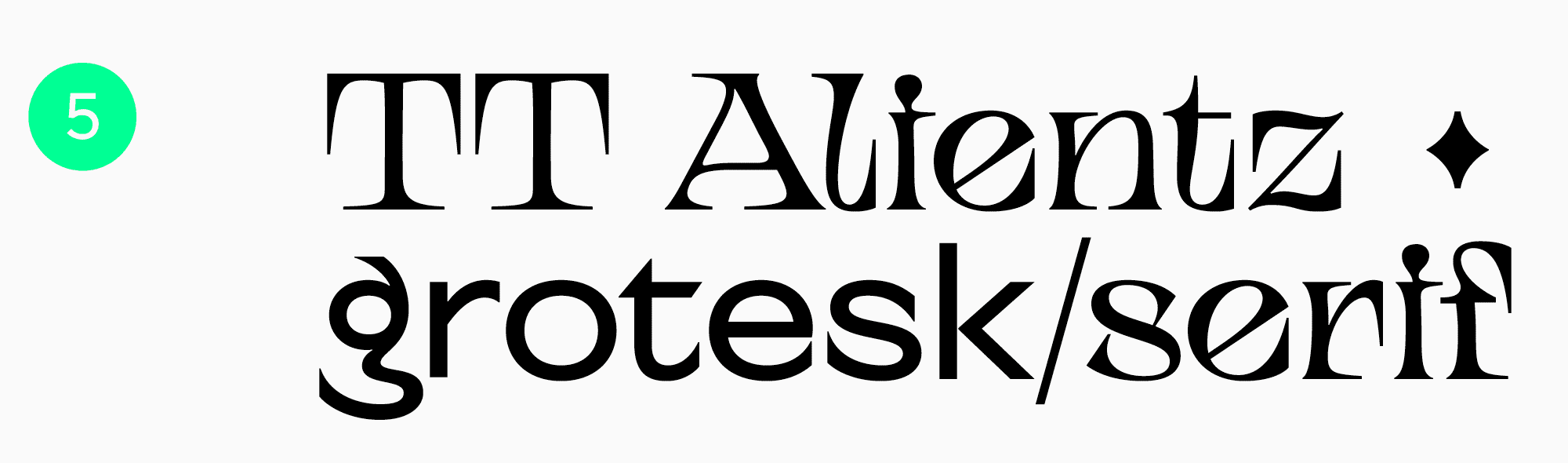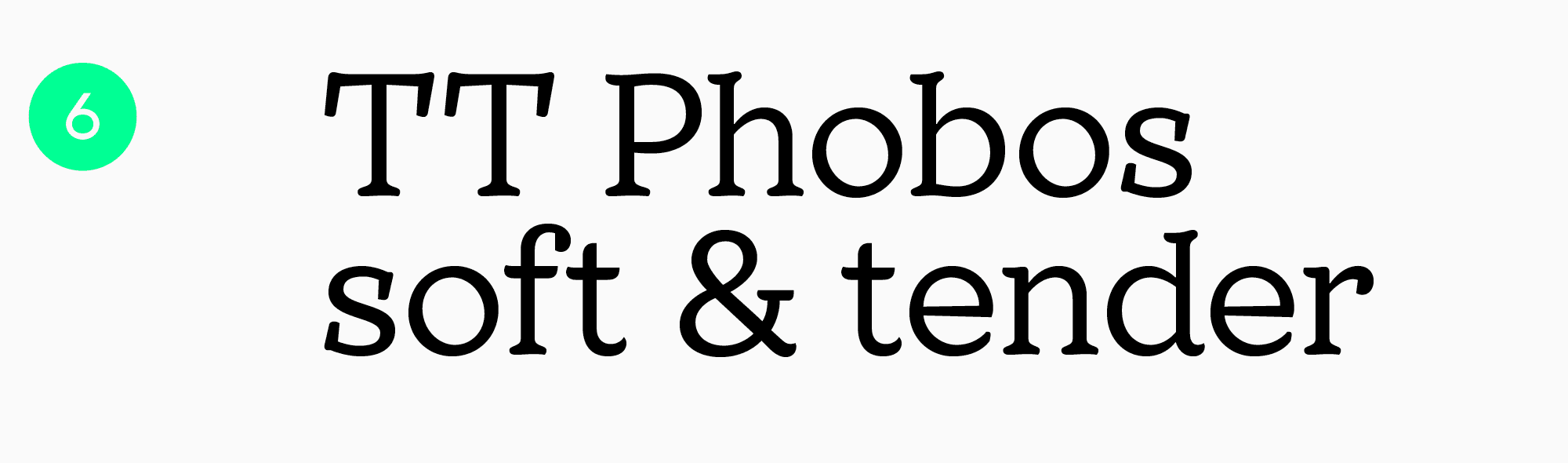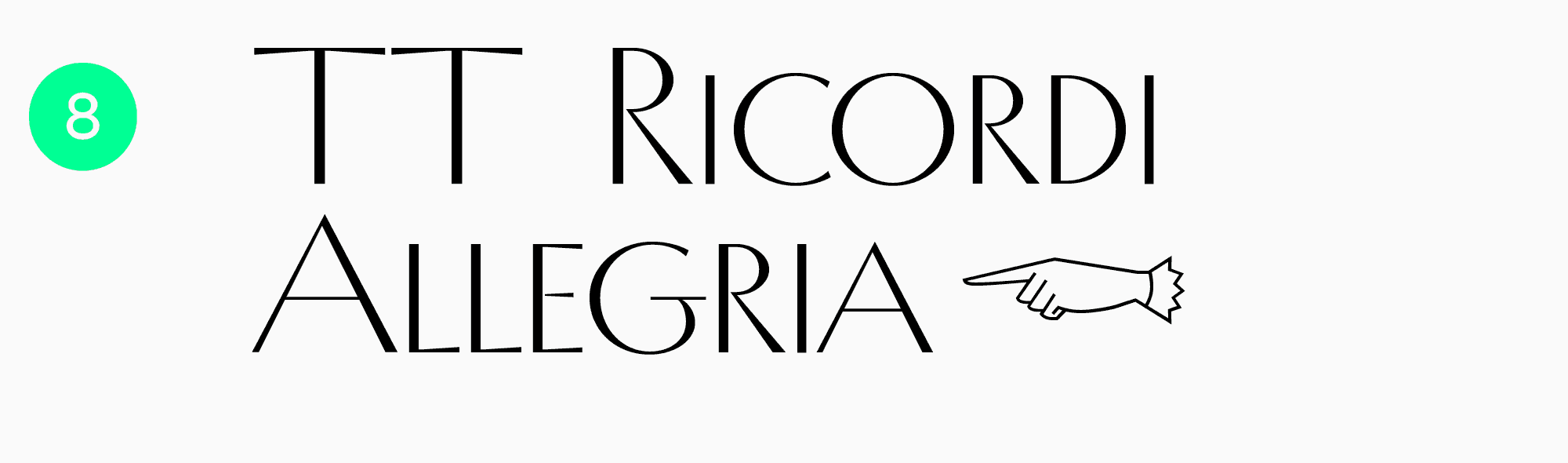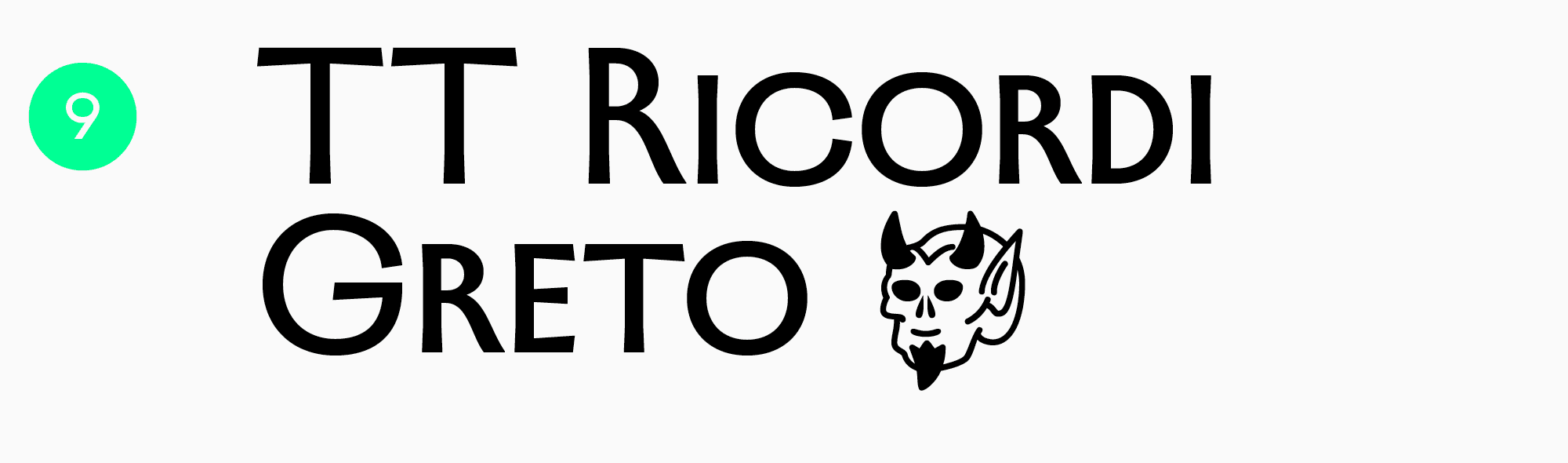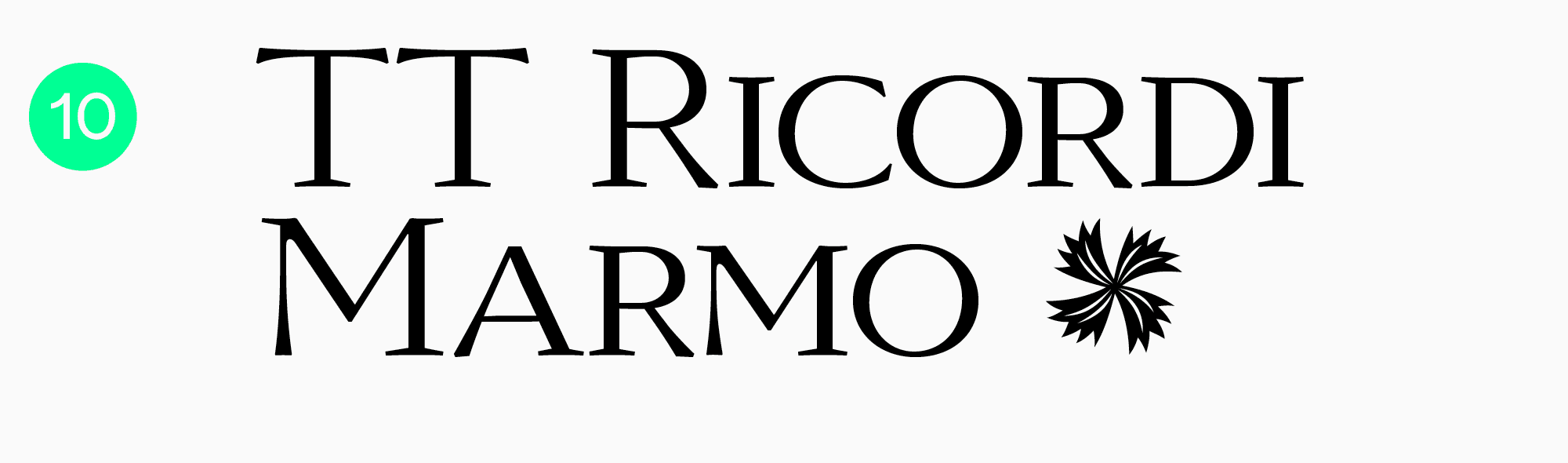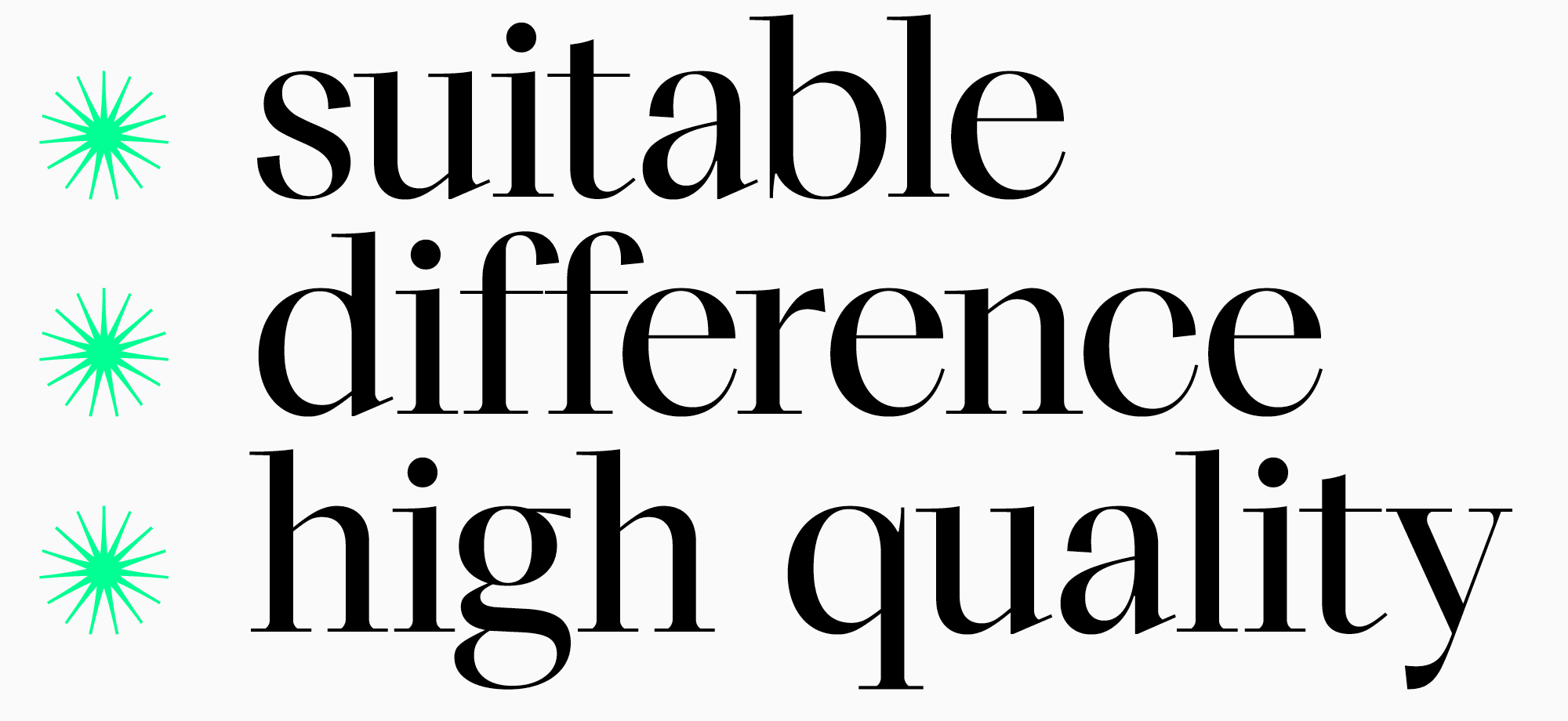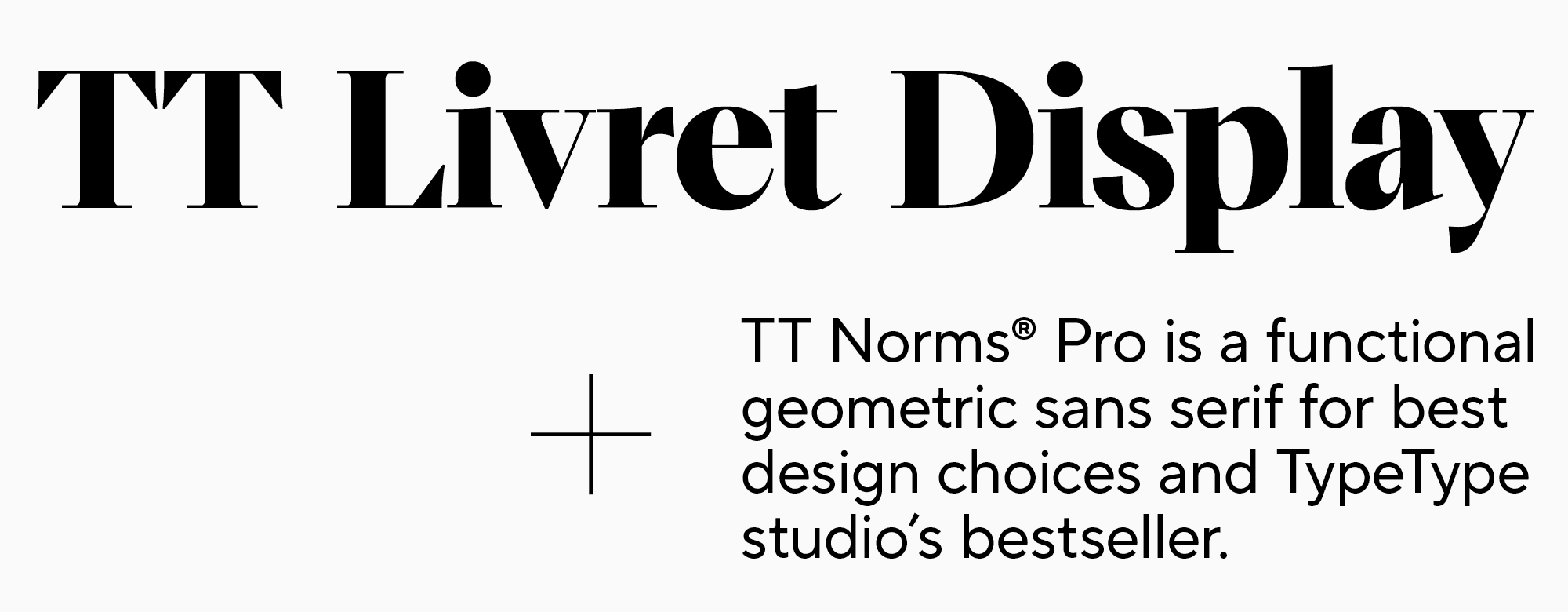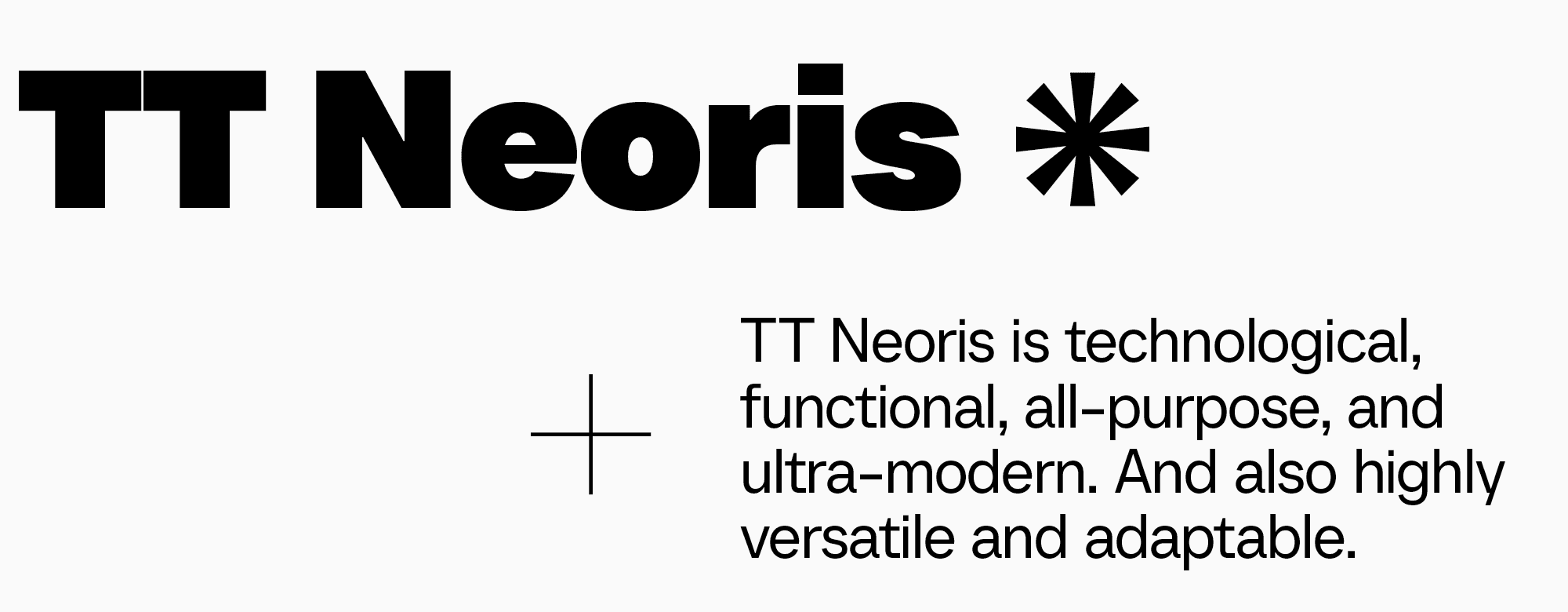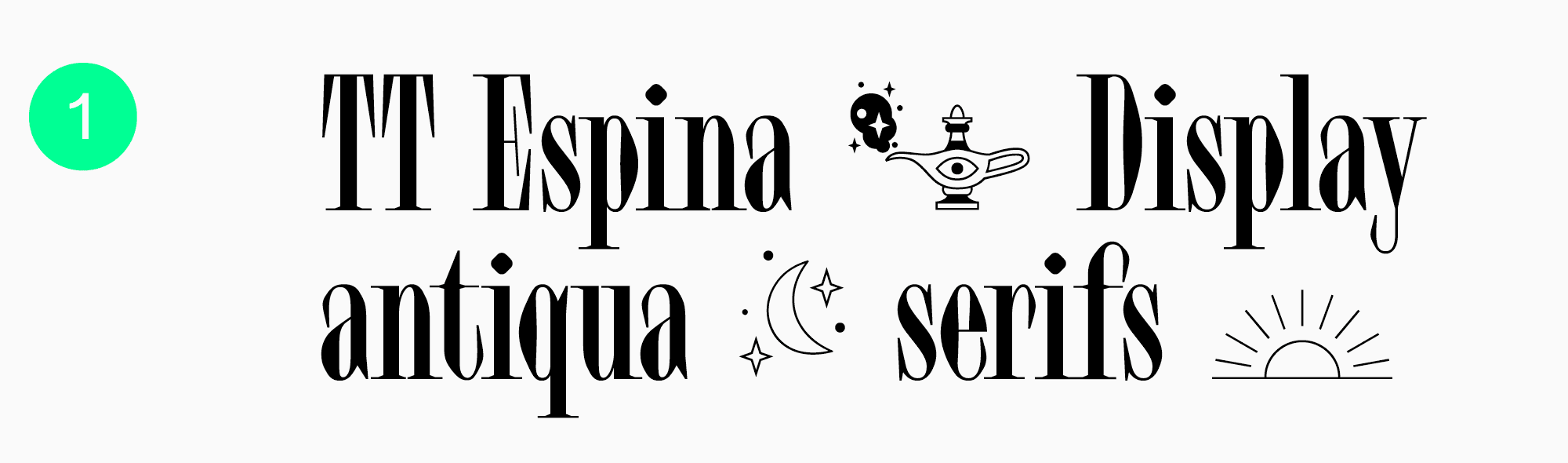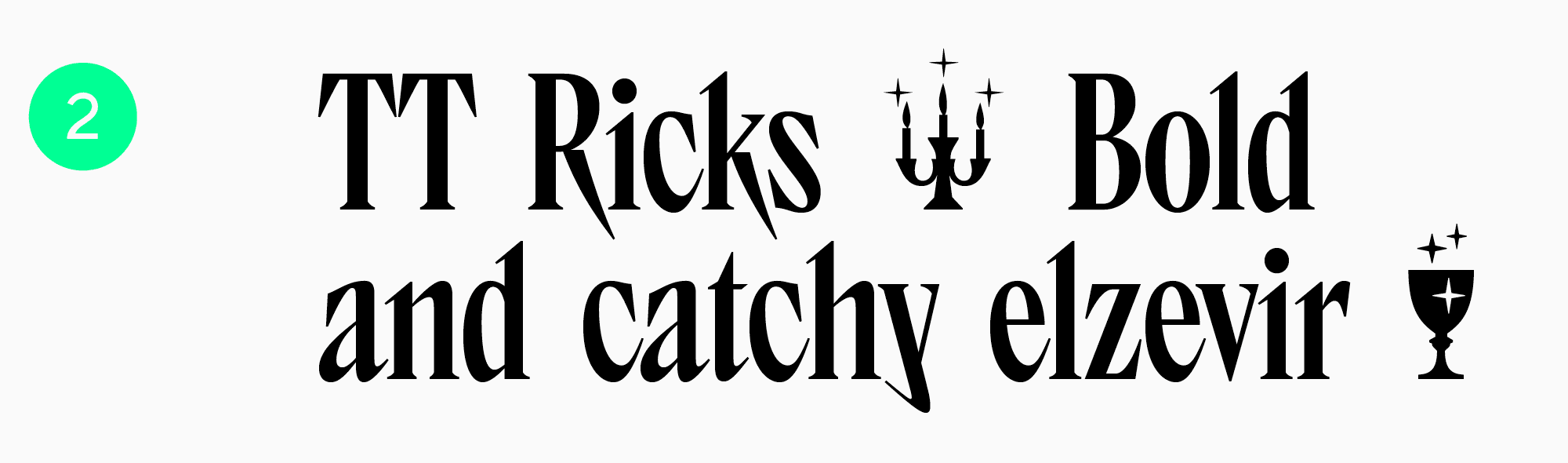
20+ лучших шрифтов для заголовков: ТОП стильных решений
Вступление
Подобрать подходящий шрифт для заголовка бывает непросто. Правильно выбранный акцидентный шрифт будет отражать ценности, идеи и общее настроение всего проекта. Он — та самая «одежка», по которой ваш проект будут встречать. А потому он должен сразу создавать нужное вам впечатление, ведь второго шанса привлечь внимание пользователя в перенасыщенном информацией мире может и не быть.
Какие шрифты для заголовков лучше выбирать и на какие критерии опираться при подборе? Рассказали в этой статье и составили список из 20+ лучших вариантов.
Какие шрифты используются для заголовков?
Все шрифты по назначению делятся на текстовые и заголовочные (акцидентные). Текстовые шрифты подходят для набора больших объемов текста: их должно быть легко и удобно читать на любых устройствах. Они более нейтральные и лаконичные на вид, без лишних деталей. Максимальный комфорт для восприятия — главный критерий при выборе такого шрифта. Текстовые шрифты используются в размере от 6 до 14-16 пунктов.
Акцидентные же шрифты предназначены для крупных надписей, заголовков, акцентов в тексте — в общем, их используют, там, где нужно привлечь внимание. Это более выразительные шрифты с ярким характером. Их графика более сложная, часто они насыщены деталями, которые интересно рассматривать. В отличие от текстовых, акцидентные шрифты используются в более крупном размере — от 14 пунктов.
Среди акцидентных можно выделить титульные шрифты. Они предназначены для оформления титульных листов, обложек и заголовков. Часто у таких шрифтов сокращенных кассовый состав, либо они состоят только из прописных букв. Используются такие шрифты в размере от 16 пунктов.
Интересно, что требования к текстовым шрифтам сформулированы гораздо четче, чем к акцидентным. Скажем больше — благодаря правильной верстке роль заголовочного может исполнить текстовый шрифт. А вот набрать большой массив текста любым акцидентным не получится. Если шрифт был задуман как заголовочный, он, скорее всего, не сможет заменить текстовый.
Получается, что акцидентным может быть практически любой шрифт. Как же тогда выбрать подходящий вариант? Давайте разбираться.
Как выбрать хороший шрифт для заголовка: несколько советов
Выбор шрифта для заголовка — субъективный процесс и напрямую зависит от целей и задач, которые перед вами стоят. Всегда подбирайте шрифт для конкретного проекта, а не просто понравившийся вам визуально вариант. Для разных проектов могут подойти абсолютно разные шрифты, единых правил здесь нет. Однако есть критерии, на которые стоит опираться.
Заголовочный шрифт должен:
• Подходить по стилю для вашего проекта, передавать эмоции и ценности, заложенные в него;
• Отличаться от основного шрифта, чтобы привлекать внимание. То, насколько сильным будет это различие, зависит от ваших целей;
• Корректно отображаться на всех устройствах. Хороший заголовочный шрифт — это технически качественный шрифт. Уделяйте особое внимание этому критерию, если выбираете бесплатный шрифт.
Как выбрать заголовочный шрифт в пару к текстовому?
Если у вас уже есть основной шрифт и вы выбираете к нему в пару акцидентный, либо выбираете шрифтовую пару, рекомендуем ориентироваться на следующие советы.
1. Выбирайте такие шрифты, которые будут эстетически и стилистически подходить для вашего проекта;
2. Определите роль каждого шрифта: какой будет основным, а какой — использоваться для акцентов? Сначала подберите «рабочую лошадку», а уже затем — акцидентную пару к нему;
3. Следуйте принципу максимального контраста. Шрифты в паре должны объединяться идеей, но при этом заметно различаться.
Если вы хотите узнать больше о принципах подбора и сочетания шрифтов, читайте нашу статью «УниверситеТТ: Урок 5. Подбор и сочетание шрифтов: теория и практика».
Процесс подбора шрифтовой пары можно сравнить с выбором наряда. Предположим, вы идете на какое-то мероприятие и в качестве базы надеваете простые джинсы. В шрифтовом гардеробе такими джинсами станет базовый гротеск, например, TT Norms® Pro. В зависимости от того, как вы его обыграете, этот нейтральный шрифт будет смотреться более формально или более расслабленно.
Если дресс-код на мероприятии серьезный и даже немного строгий, в пару к джинсам можно надеть пиджак — тогда весь образ станет более официальным. Такой пиджак в мире шрифтов —антиква TT Livret Display. Это элегантный шрифт, который контрастирует с базовым TT Norms® Pro, при этом отлично с ним сочетается.
Как использовать один и тот же шрифт для текста и заголовков?
В условиях ограниченных ресурсов можно и вовсе взять всего один шрифт и использовать его в разных кеглях и весах для основного текста и заголовков. В этом случае нужно выбрать хороший текстовый шрифт, который, в первую очередь, удобно читается в небольшом размере, но при этом интересно выглядит и в более крупном и создает необходимый контраст при выборе более жирного начертания.